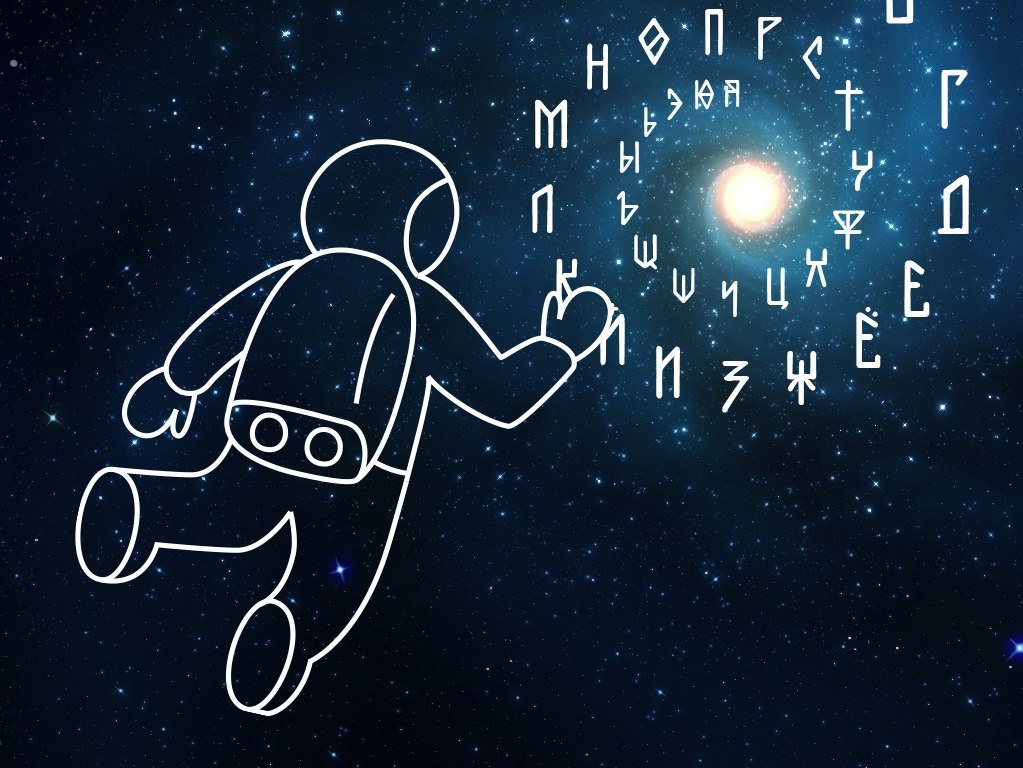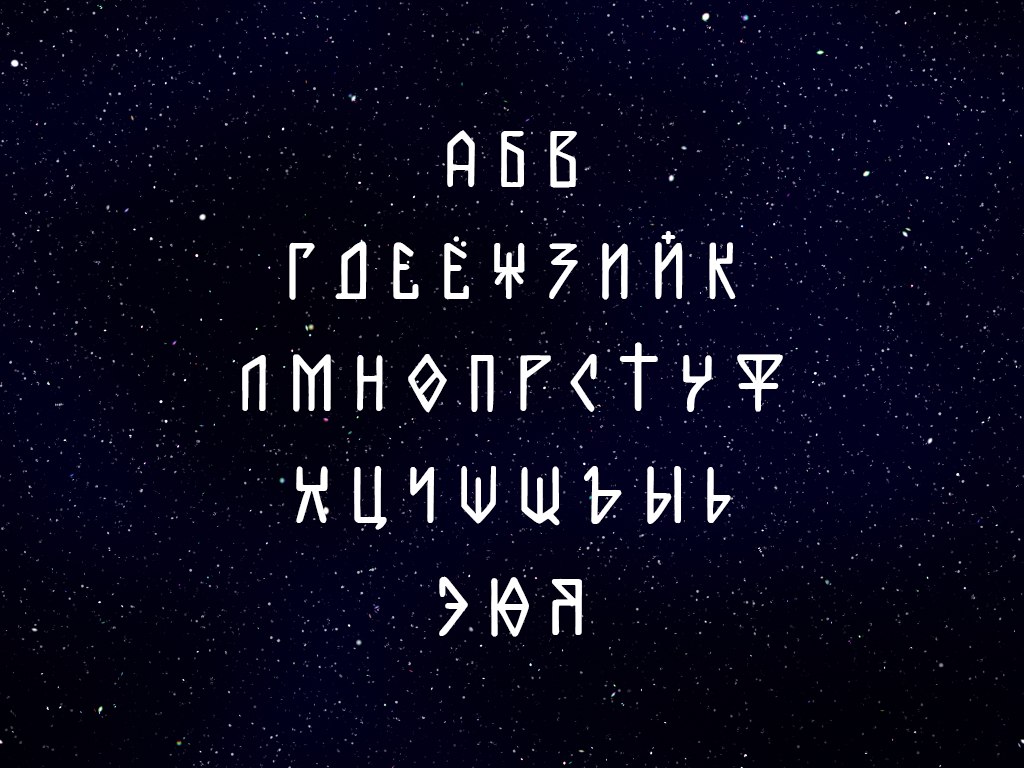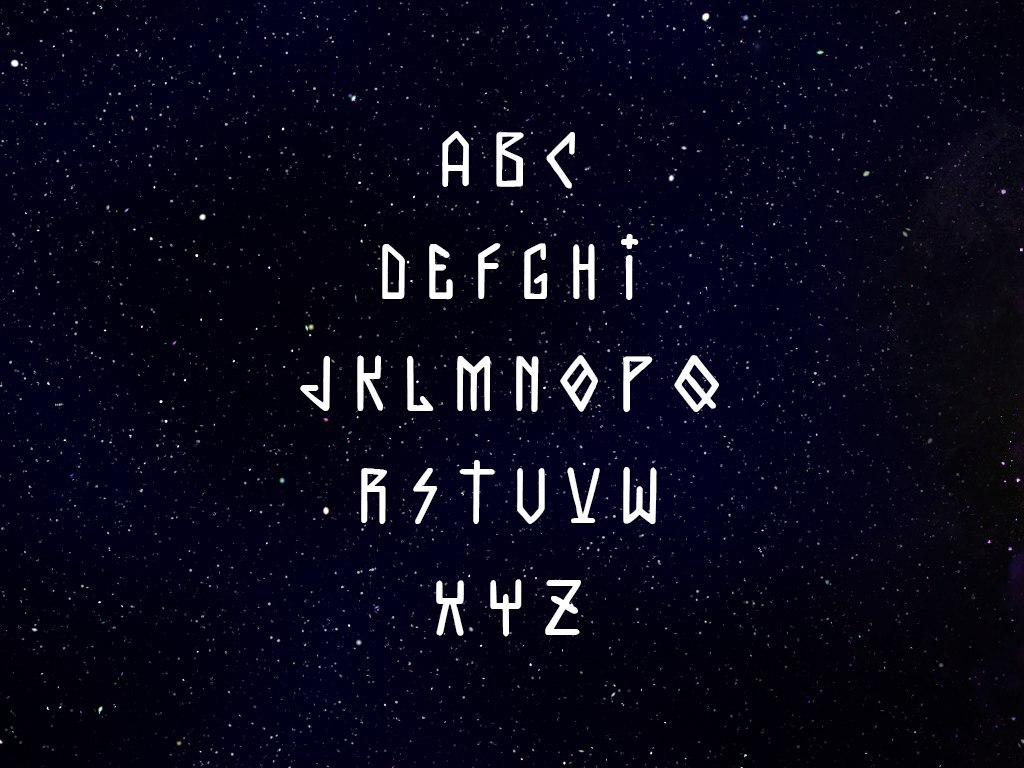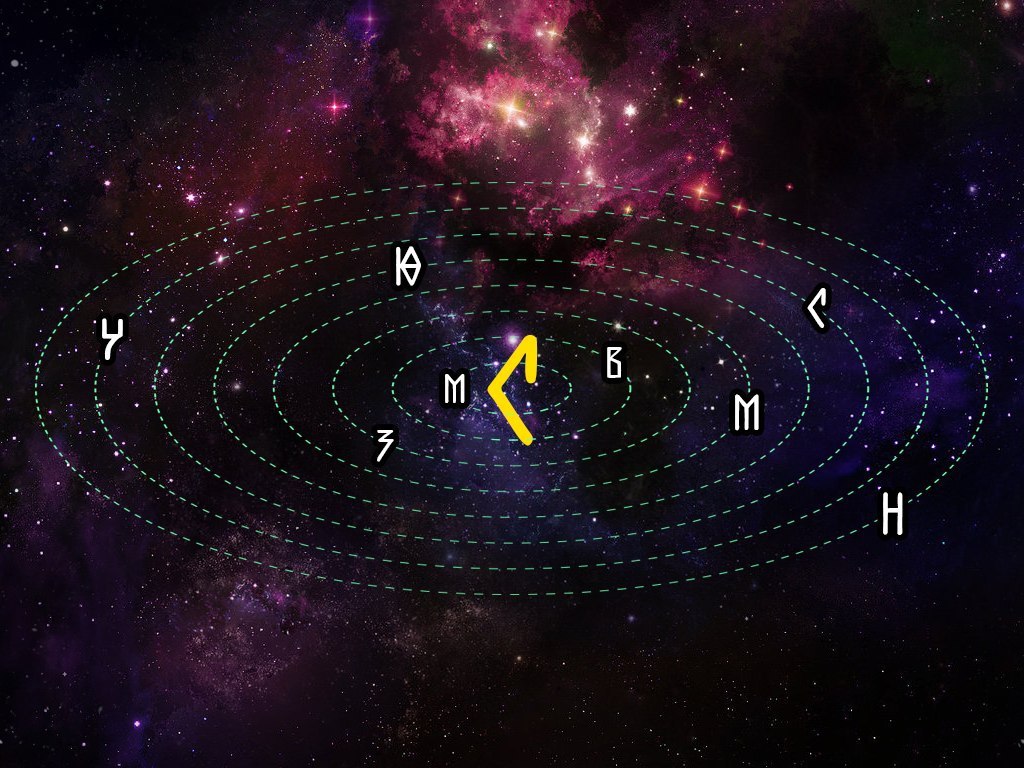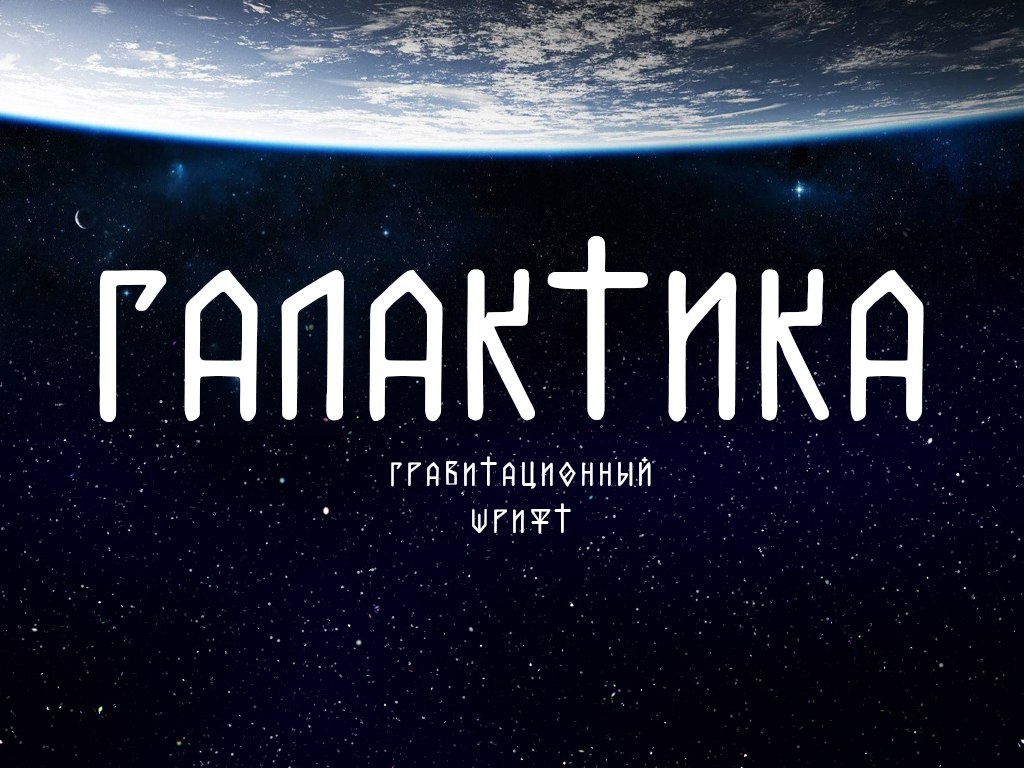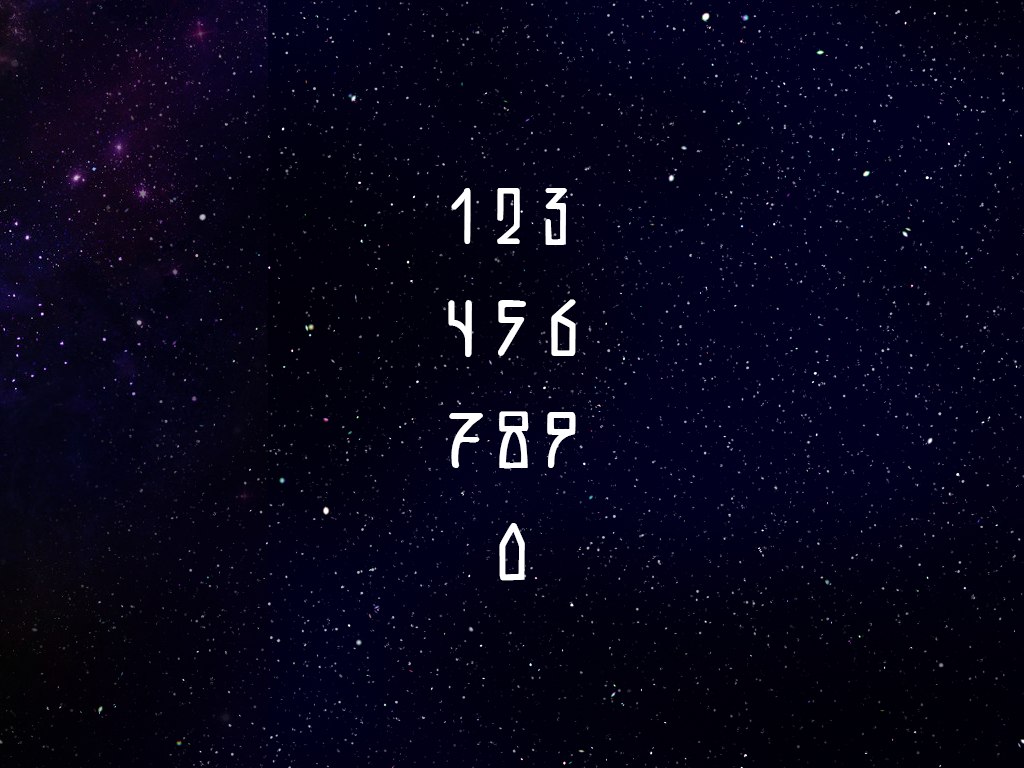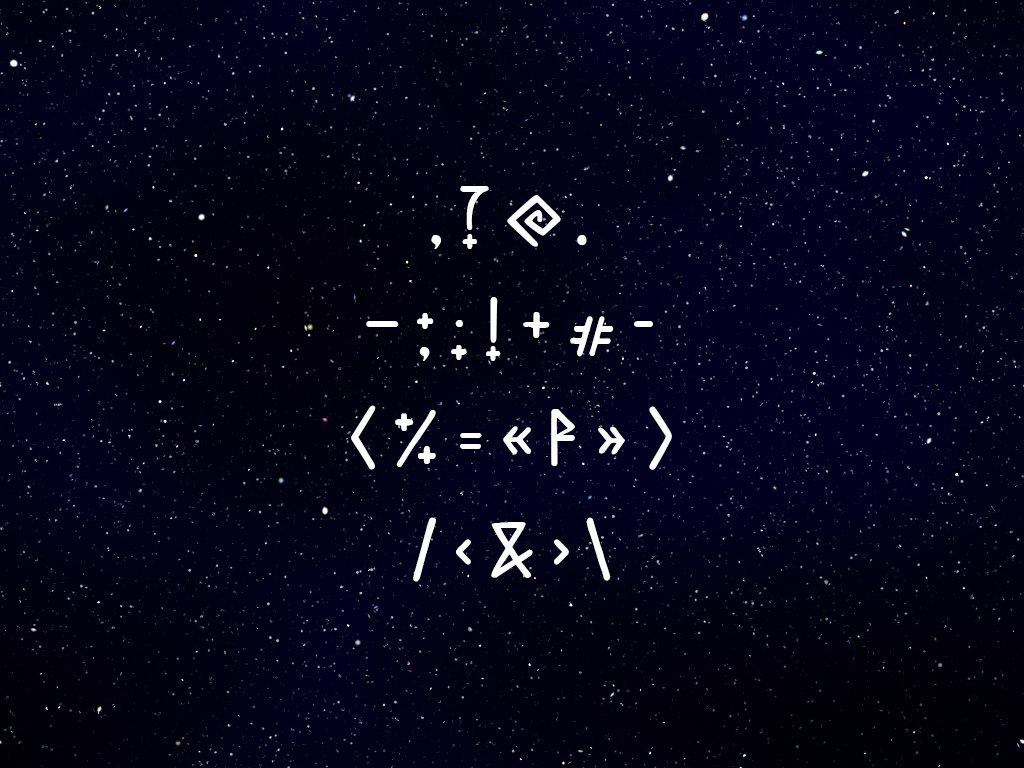
ШРИФТ | ГАЛАКТИКА
Еще один декоративный шрифт от Миши Панфилова. Галактика — декоративный кириллический шрифт со всеми основными спецсиволами (знак рубля тоже есть).
Кириллица –